Schriftausstellung
Asien
Von der arabischen Halbinsel bis zum Pazifik leben mehr Schriftsysteme nebeneinander als auf irgendeinem anderen Kontinent — Alphabete, Silbenschriften und Logogramme prägen je eigene Lesegewohnheiten.
Asien ist ein Kontinent vieler Schriftfamilien. Im Westen begegnen sich Hebräisch und Arabisch — eng verwandt, beide von rechts nach links geschrieben. Östlich davon blüht die indische Sprachfamilie mit Devanagari, Tamil und vielen Schwestern, in denen jedes Zeichen für eine Silbe steht.
Im Norden trifft das kyrillische Alphabet auf das Mongolische, das traditionell senkrecht von oben nach unten verläuft. Ostasien lebt mit Han-Zeichen, japanischen Silbenschriften und koreanischem Hangeul, während Khmer und seine Verwandten Südostasien prägen. Dazu kommen zahllose regionale Schriften — teils eigenständig, oft Ableitungen größerer Systeme.
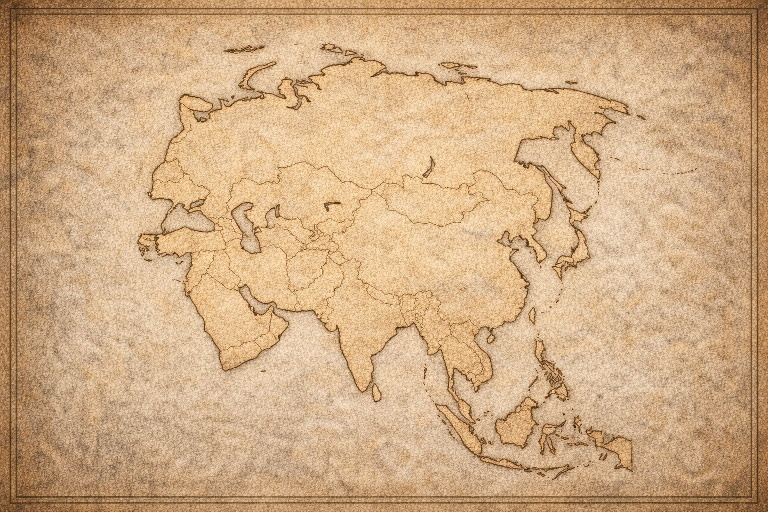
Schriften Asiens auf einen Blick
Karte der Schriftregionen Asiens
Eine Karte, viele Welten
Die einzelnen Regionen sind anklickbar: vom Hebräischen am Mittelmeer über das Arabische, das indische Mosaik und Zentralasien bis nach Ostasien. Jede Fläche öffnet eine eigene Schrifttradition mit Jahrhunderten Geschichte.